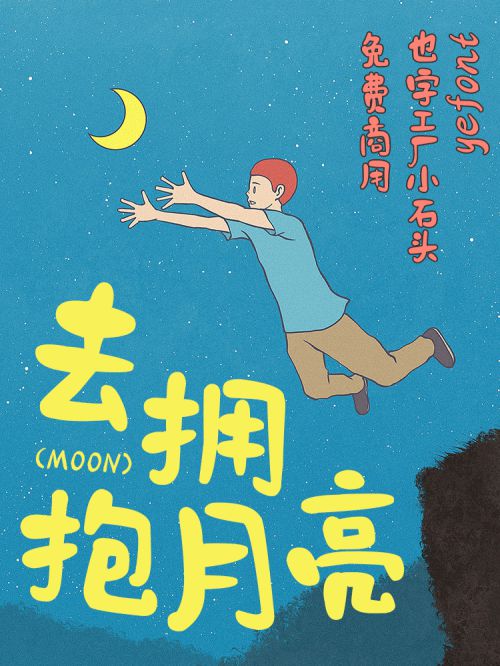
也字工厂小石头
小石头字体是一款兼具力量感与亲和力的创意黑体。字形方正稳健,重心居中设计确保视觉平衡,中宫适中的比例让字体在各种字号下都保持清晰易读。其独特之处在于笔型融入圆润转角,搭配粗重均匀的笔画线条,圆头笔画设计更添几分俏皮感,仿佛一颗颗精心打磨的小石头,既有方正棱角的稳重,又不失圆角带来的柔和。特别的是,笔画采用断开式处理,巧妙打破传统黑体的紧凑感,为字体注入灵动气息,让每个字符都如同独立又相连的小石块,富有节奏感与设计巧思。适用于儿童读物、包装设计、品牌LOGO等场景,是兼具实用性与创意的理想字体选择。